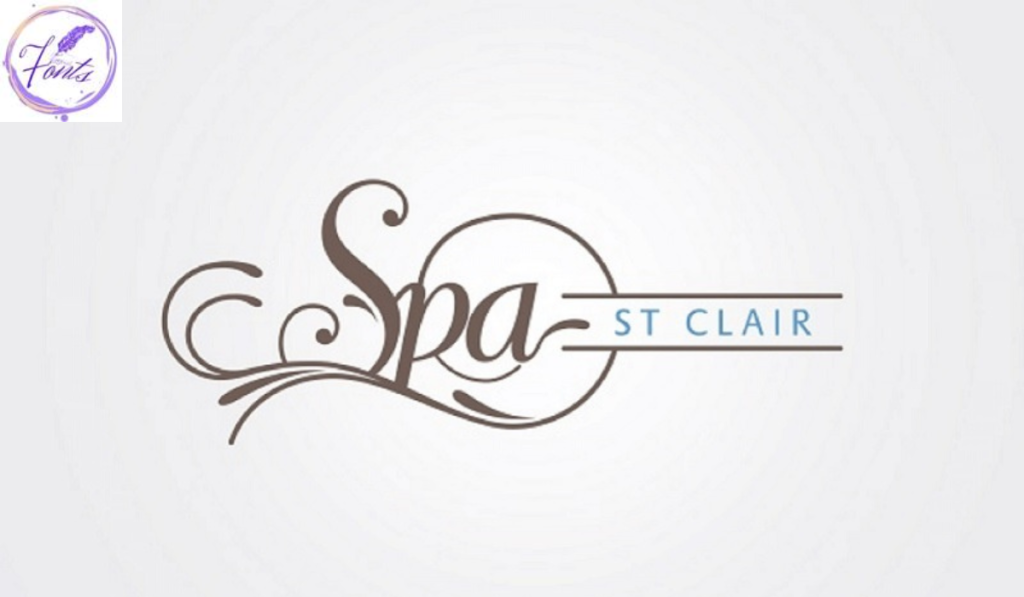
Top 10 font chữ Spa đẹp cập nhật 2024
Tác giả: Robert E. Leuschke
Ngày phát hành: 2018
Ngôn ngữ: Tiếng Việt và một số ngôn ngữ khác
Bộ Font: Great Vibes
Phân loại: Vui vẻ, Thư giãn, Lãng mạn
Kiểu chữ: Viết tay
Độ dày: Hairline, Thin, Light, Regular, Medium, Bold, Black, Fat
Khi nói đến việc tạo ra một không gian thư giãn và chào đón trong ngành spa và massage, việc lựa chọn font chữ spa phù hợp là rất quan trọng. Các font spa được thiết kế để phản ánh sự nhẹ nhàng, tinh tế và tạo cảm giác thư thái cho khách hàng. Những font này thường thuộc kiểu chữ viết tay (script), chữ không chân (sans-serif), có đường nét mềm mại, dễ chịu, phản ánh đúng tinh thần của một không gian làm đẹp và chăm sóc sức khỏe, giúp khách hàng cảm thấy thoải mái ngay từ cái nhìn đầu tiên. Đọc bài viết sau đây để xem và tải top 10 font chữ spa thu hút khách hàng cập nhật tháng 7/2024.
Top 10 font chữ spa đẹp năm 2024
Font chữ spa đẹp nhất 2024 – Font Great Vibes
Great Vibes, thiết kế bởi Robert E. Leuschke và ra mắt vào năm 2012, là một phông chữ kỹ thuật số nổi bật trong giới thiết kế đồ họa. Với đường nét thanh thoát và phong cách quyến rũ, phông chữ này không chỉ phù hợp cho các dự án sáng tạo mà còn là lựa chọn hoàn hảo cho các thương hiệu trong lĩnh vực thẩm mỹ, spa, và những không gian cần sự sang trọng.
Font Montserrat
Montserrat, thiết kế bởi Julieta Ulanovsky và ra mắt vào năm 2011, là phông chữ sans-serif hình học tinh tế và hiện đại. Được lấy cảm hứng từ những áp phích, bảng hiệu và cửa sổ sơn cổ điển ở Buenos Aires, Montserrat trở thành lựa chọn ưu tiên cho các dự án đồ họa và web, đồng thời là biểu tượng của sự sang trọng cho các thương hiệu thẩm mỹ, spa và không gian cần sự tinh tế.
Font 1FTV Roxie Rossa
Font 1FTV Roxie Rossa là một font chữ serif hiện đại với phong cách đơn giản và tối giản. Font được thiết kế bởi ToniStudio, mang đến cảm giác cổ điển nhưng vẫn rất thời thượng. Với đường nét mềm mại và thanh thoát, 1FTV Roxie Rossa rất thích hợp cho các thiết kế như logo, tạp chí, spa và nội dung trên mạng xã hội.
Font SVN Hamstring
Font SVN Hamstring là một font chữ viết tay mềm mại, mang đến cảm giác gần gũi và tự nhiên. Với những đường cong uyển chuyển và phong cách phóng khoáng, SVN Hamstring tạo ra một không gian thư giãn, rất phù hợp cho các thiết kế liên quan đến Spa và thẩm mỹ viện.
Font chữ spa viết tay Sverige Script
Font Sverige Script là một font chữ viết tay tinh tế, mang đến vẻ đẹp nhẹ nhàng và thanh thoát. Với những đường nét mềm mại, font này tạo ra cảm giác gần gũi và tự nhiên, rất phù hợp cho các thiết kế liên quan đến Spa và thẩm mỹ viện.
Font Pacifico
Great Vibes là một phông chữ viết tay đầy sức sống, mang đến cảm giác tươi mới và vui vẻ. Phông chữ này rất được ưa chuộng trong thiết kế spa và thẩm mỹ, tạo ra không khí thân thiện và gần gũi. Great Vibes là lựa chọn hoàn hảo để xây dựng không gian độc đáo và thu hút cho các dịch vụ làm đẹp.
Font chữ spa serif có chân – Font Waschkueche
Font Waschkueche là một font chữ mang phong cách hiện đại và độc đáo, với những đường nét rõ ràng và mạnh mẽ. Đặc điểm nổi bật của font này là sự kết hợp giữa sự tinh tế và cá tính, tạo nên một ấn tượng mạnh mẽ và thu hút.
Font chữ việt hóa Fairyland
Font Fairyland là một font chữ mang phong cách tinh tế và thanh lịch, rất phù hợp cho các thiết kế liên quan đến Spa và thẩm mỹ viện.
Font Hello Paris Việt hóa
Font Hello Paris thuộc dòng serif hiện đại, kết hợp giữa sự sang trọng và tính thẩm mỹ tinh tế. Nó bao gồm một phông chữ script mang phong cách chữ ký tinh tế và một phông chữ serif in hoa đầy sang trọng. Sự kết hợp này không chỉ tạo ra một sự tương phản hoàn hảo mà còn giúp nâng cao giá trị thương hiệu cho các sản phẩm và dịch vụ cao cấp như spa
Font Quicksand
Font Quicksand có đường nét mềm mại và thanh thoát, tạo cảm giác nhẹ nhàng và hiện đại. Phù hợp cho các thiết kế như Spa Thẩm mỹ, Quicksand mang đến không khí tinh tế và dễ đọc, đem lại trải nghiệm thiết kế tinh tế và thư giãn.